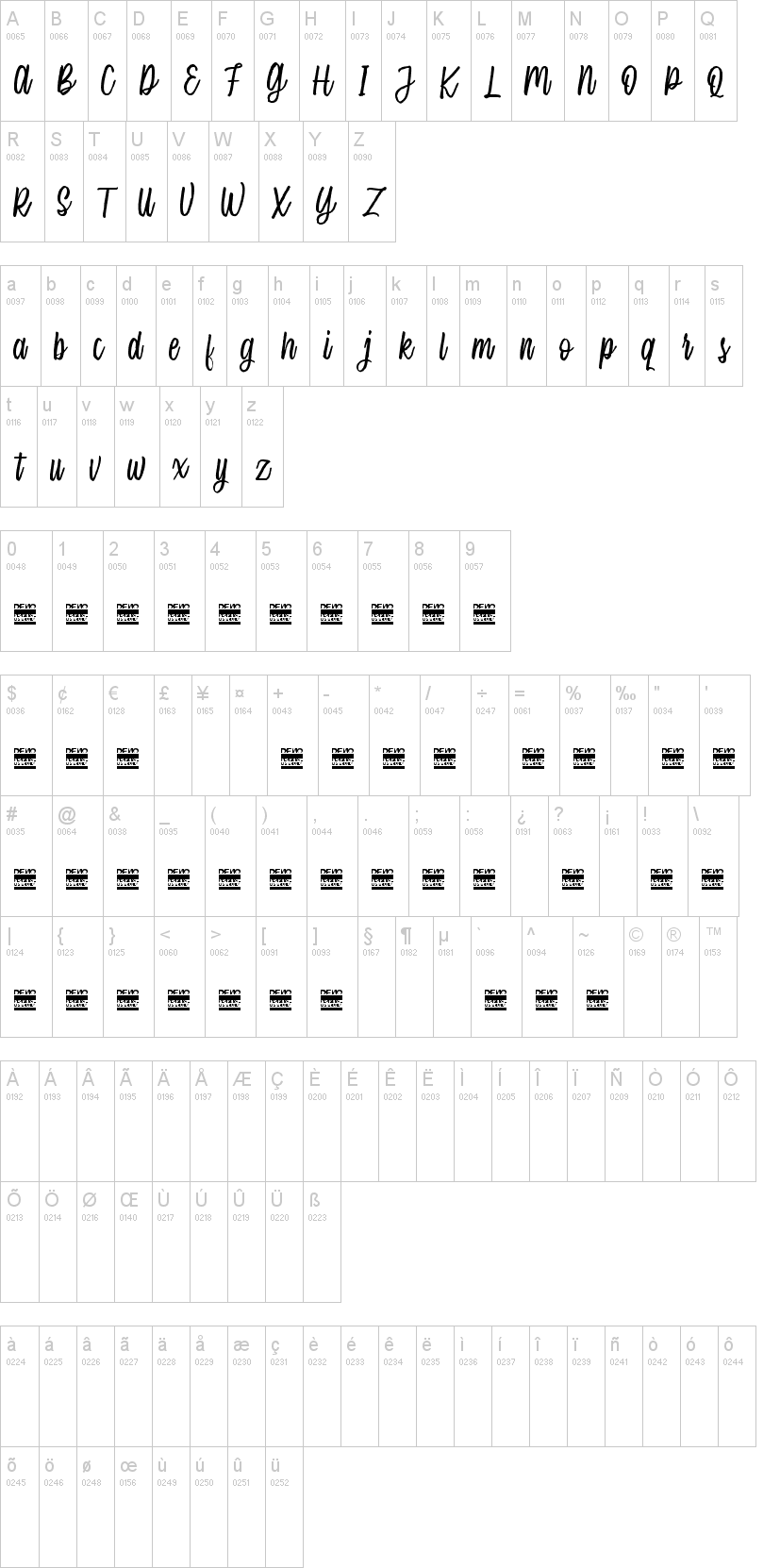
Single Brand 是一种商业字体,由品牌设计公司 Brand Design Co. 创作发行。该字体的设计灵感来源于品牌设计的理念,旨在为品牌提供专属的视觉形象。Single Brand 字体设计简洁大方,较为适用于标题、标语等场合,字形清晰明了,线条流畅优美,让品牌信息更加醒目。Single Brand 字体系列中包含多个字重和风格,可以适应不同的设计需求,具有较高的可应用性。该字体适用于广告、标志、品牌包装、网站设计等多个领域,是一种优秀的商业字体选择。内容介绍
Single Brand是一款非常不错的手写艺术字体,具有很好的视觉感,适合于文化类的宣传设计、商业类品牌的广告和产品包装设计以及个性化文字排版等较多场景。